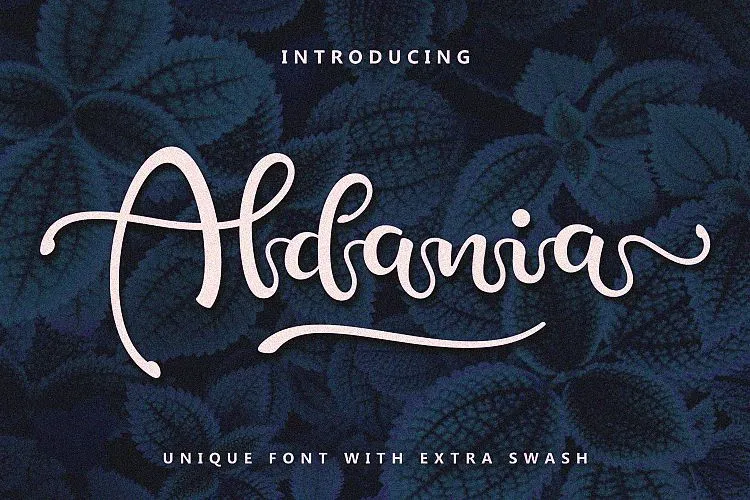
Aldania Script Font – Download Grátis
Aldania Script é uma linda fonte script moderna criada pela 24Design. Com seu estilo ornamental e uma baseline que dança entre linhas, Aldania traz um toque único de originalidade ao seu design. A fonte tem detalhes cuidadosamente trabalhados, reminiscentes de uma arte manual da caligrafia, proporcionando um aspecto encantador e divertido para qualquer projeto criativo. Seja ela usada em cartões de convite, materiais de marca ou até mesmo em postais pessoais, Aldania Script irá adicionar um toque especial à sua produção. Este é o tipo de fonte que te fará querer criar mais projetos únicos e agradáveis para poder experimentar todas as suas possibilidades.